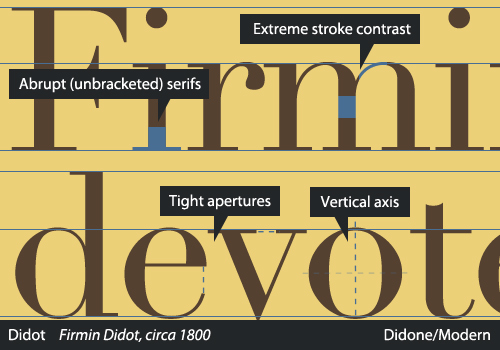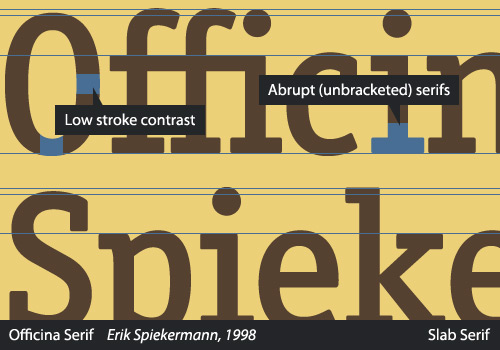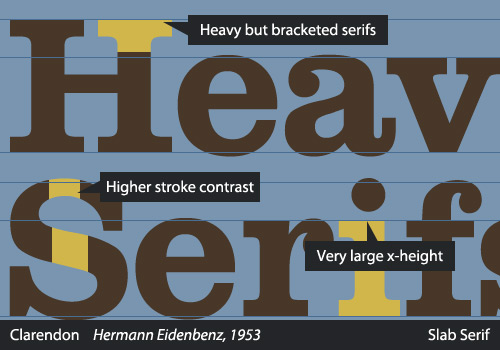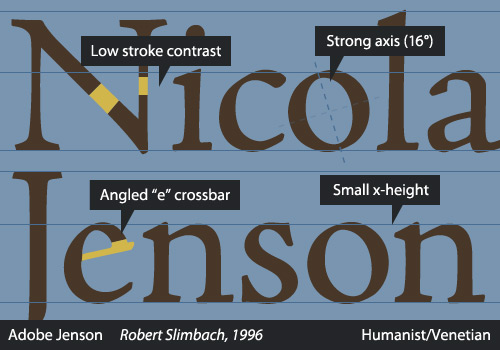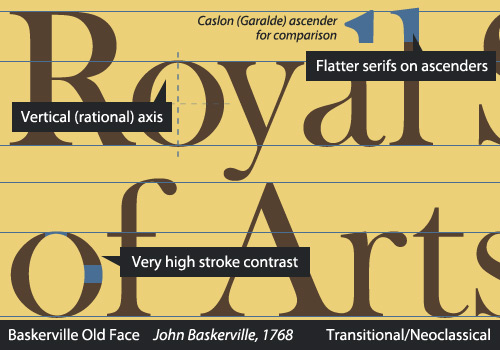
В своей предыдущей статье для Smashing Magazine («В чем разница между типографикой и дизайном надписей») я писал о том, что понимание типографской терминологии может помочь правильно оценить как искусство типографики, так и искусство создания надписей. Эта новая статья также имеет отношение к терминологии, возможно в большей степени, чем к тому привыкло большинство дизайнеров, а заголовок статьи отражает все то, о чем в ней пойдет речь.
Все знают о гротесках и антиквах, брусковых и рукописных шрифтах, но большинство классификаций оказываются гораздо более подробными. Классификация шрифтов, будучи в целом полезной, часто оказывается излишне сложной, запутанной и даже противоречивой. В этой статье я отсеял ряд сложностей, приведя их к более удобоваримому формату, что сделало материал промежуточным звеном между эссе по основами типографики и занудной статьей для искушенных профессионалов – идеальный вариант для практикующего дизайнера.
Зачем классифицировать шрифты?
Существует определенное интеллектуальное удовольствие в обладании знаниями, в особенности знаниями в области выбранной сферы учебы или работы. Что, вероятно, более важно, существует мнение, согласно которому знания, на первый взгляд лишенные практической ценности, придают дизайнеру больший вес. Если следовать этой логике, то, что вы прочтете – абсолютно непрактично. Этот материал поможет лишь лучше обосновать свое дизайнерское решение.
Сцена из фильма о 1920-х, в которой используется шрифт, созданный в 1975
Хорошее понимание истории типографики поможет вам избегать типографических анахронизмов – пусть большинству людей они и не видны, эти ляпы не укроются от взгляда множества дизайнеров, что и продемонстрировал Марк Симонсон (Mark Simonson) в своей статье о картине «Артист», в 2012 году получившей Оскара за лучший фильм, и в других своих типографических обзорах популярных фильмов и шоу.
Изучение классификации шрифтов, однако, не всегда связано лишь с историей типографики. Классификация также полезна для выбора сочетающихся шрифтов в рамках единого проекта – иногда такой подбор может основываться на исторической близости времени создания шрифтов, но часто учитывает и степень близости показателей ряда характеристик, объединяющих разные гарнитуры, таких как ось овалов и рост строчных. В некоторых случаях, когда несоответствия между такими характеристиками оказываются незначительны, комплементарными друг другу могут стать очень разные гарнитуры.
Что еще важнее, эта статья не только будет знакомить вас с общей историей типографики и общеупотребительной терминологией, но и поможет научиться искать и распознавать важные характеристики шрифтов и неисчерпаемое множество мельчайших деталей, делающих гарнитуры уникальными, а также предложит полезные описания стилей шрифтов.
Системы классификации шрифтов
За прошедшее столетие было предложено сравнительно немного систем классификации шрифтов. Большинство из них по всеобщему мнению субъективны и несовершенны, многие к тому же используют одни и те же термины для описания внешне сходных, но различных по своей природе классов шрифтов. Невозможность создания по-настоящему всеобъемлющей классификации привела к тому, что многие попросту оставили попытки как бы то ни было классифицировать шрифты – существует слишком много переменных, препятствующих созданию адекватной, практически полезной системы. В сущности, классификации описывают шрифты, а не определяют их. Такой подход не гибок и полезен в качестве вспомогательной помощи, а не руководства к действию. Однако, по причинам, высказанным ранее, я считаю, что и в таком подходе есть своя ценность. Ниже я приведу несколько примеров.
Главная «официальная» система классификации на сегодняшний день – система Vox-ATypI. Изначально составленная в 1954 году Максимильеном Воксом (Maxmilien Vox), в 1962 она была заимствована Международной Типографской Ассоциацией (Association Typographique Internationale – ATypI), которая внесла в нее небольшие поправки по включению в классификацию Гэльских шрифтов (семья шрифтов, разработанных для записи ирландского языка) как отдельной категории на конференции 2010 года (которая проводилась, соответственно, в Дублине). Согласно классификации Vox-ATypI, все шрифты разбиваются на 11 базовых категорий с дальнейшим делением внутри каждой отдельной категории. Отличный обзор этой классификации дает статья из Википедии.
Британские Стандарты Классификации Шрифтов, принятые в 1967 году, также основываются на классификации Вокса. По сравнению с последней они несколько упрощены и остаются неизменными с момента возникновения.
Роберт Брингхерст (Robert Bringhurst) в своей книге «Основы стиля в типографике», которая стала практически стандартом современной типографической литературы, группирует гарнитуры по категориям, близким к периодам в истории искусств – например, Барокко, Рококо, Романтизм и др. Будучи дизайнером книг, Брингхерст фокусируется на текстовых гарнитурах и практически игнорирует выделительные шрифты.
Другие классификации носят куда более обобщенный характер. Более ранняя система французского типографа Франсуа Тибодо (Francis Thibaudeau), которая послужила базой для появившейся впоследствии более подробной классификации Вокса, включает четыре основные категории: Антиквы (шрифты с засечками), Египетские шрифты (брусковые шрифты), гарнитуры Didot и Elzevir (шрифты с треугольными засечками). Преподавая в Королевской Академии Изящных Искусств в Гааге, Геррит Нордзей (Gerrit Noordzij) придерживался утверждения о том, что шрифты есть естественное продолжение практики рукописного письма, и обучал студентов типографике, объединяя в одну группу большое количество вариантов начертания букв, которые можно воспроизвести с помощью перьевой или шариковой ручки, а также группируя вместе типы начертания по длине штриха (долгие/прерывистые штрихи) – при этом в каждой из категорий оказывались как гротески, так и антиквы.
Это всего лишь несколько способов, которые использовались при попытках классифицировать шрифты в течение многих лет. В этой статье из двух частей я объединю несколько различных методик систематизации и покажу вам то, что по меньшей мере в общих чертах принимается в качестве признанной системы классификации шрифтов (хотя разумеется всегда будут те, кто будет придерживаться какого-нибудь крайне необычного метода классификации, или те, кто будет отрицать целесообразность использования какого бы то ни было метода в принципе).
На сегодня, пожалуй, все
Поздравляю всех тех, кто добрался до этой части статьи! Теперь вы обладаете твердым пониманием основ классификации шрифтов, если, конечно, речь идет об антиквах, и сможете распознавать важные отличительные черты, определяющие индивидуальность той или иной гарнитуры. В соответствии с историей развития типографики, мы дошли до середины XIX века, и впереди нас ожидает немалое количество гротесков и рассуждения о некоторых других выделительных шрифтах. Мы преодолели только половину пути, так что если вам понравилось, жду вас во второй части статьи!